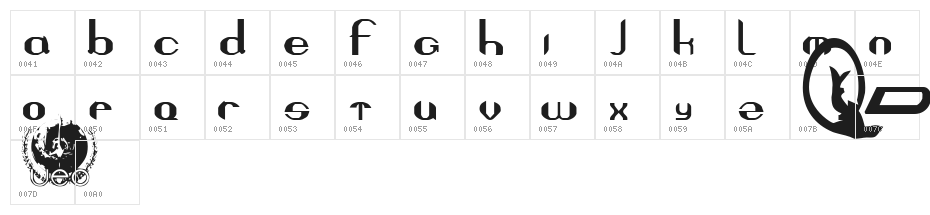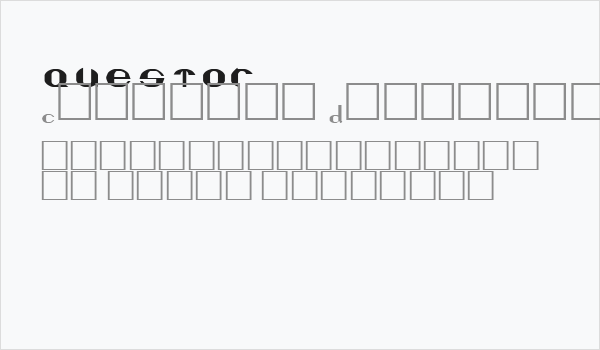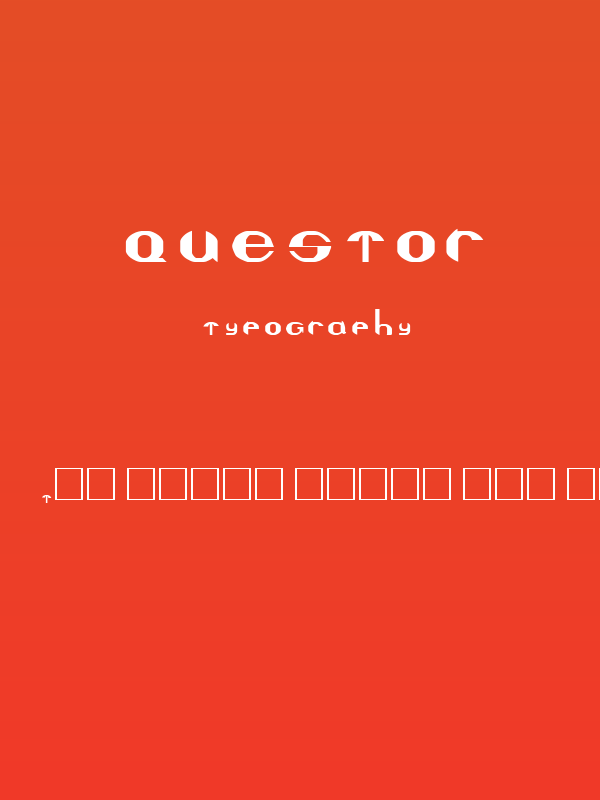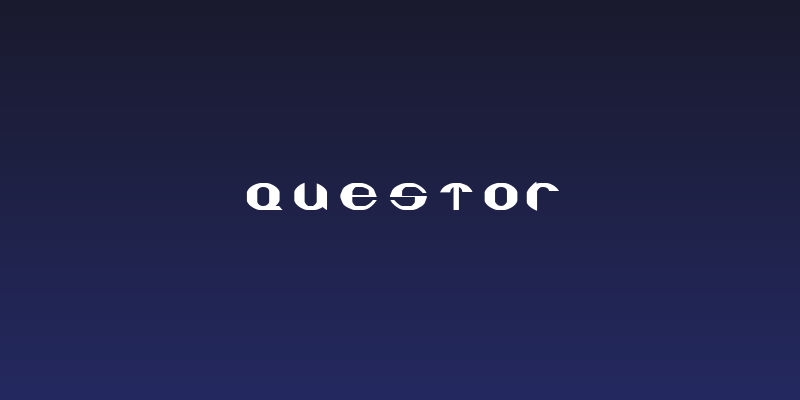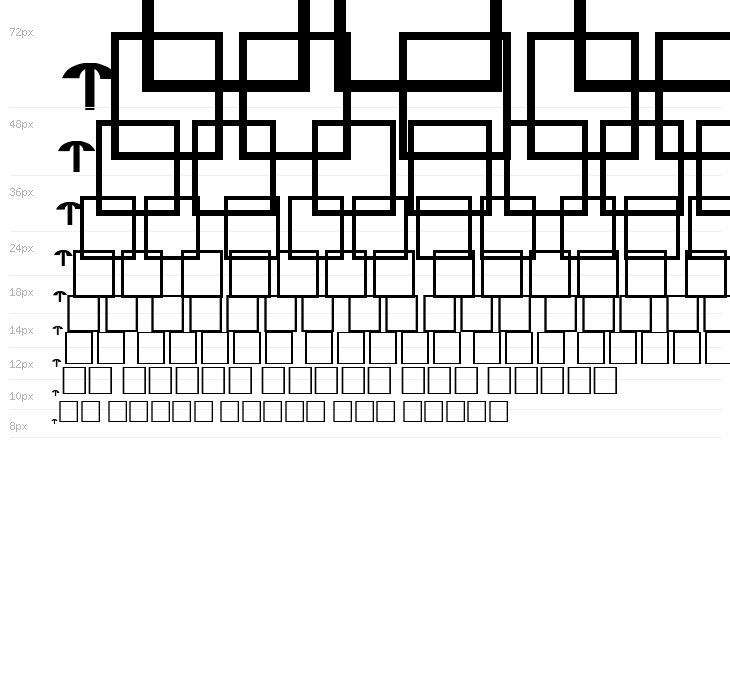
QUESTOR Font
✎ Quirky
| Gesamtstil | Futuristic, Geometric |
| Anwendungsfall | Headlines, Logos, Branding |
| Vorgeschlagene Projekte | Ideal for tech branding, digital media, futuristic designs, and innovative product packaging. |